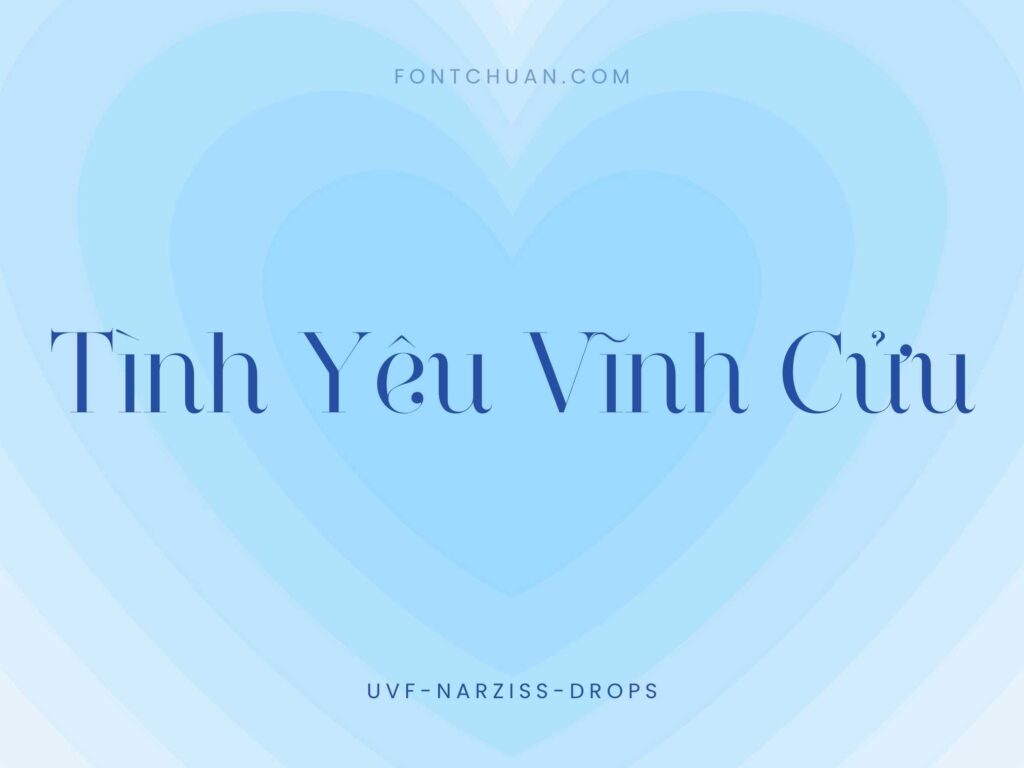
Font UVF Narzissdrops Việt Hóa
Narziss Drops là một phông chữ serif độc đáo và đầy nghệ thuật, được thiết kế bởi Hubert Jocham. Phông chữ này nổi bật với các chi tiết trang trí phức tạp và nét thanh đậm xen kẽ, tạo ra một phong cách sang trọng, lãng mạn và quyến rũ. Đặc điểm hình dạng của Narziss Drops là các đường nét hoa mỹ, uốn lượn tinh tế và sự kết hợp giữa các yếu tố truyền thống và hiện đại, giúp tối ưu hóa không gian và tạo ấn tượng thị giác mạnh mẽ.
Font này phù hợp cho các ứng dụng như thiệp mời, logo thương hiệu cao cấp, bìa sách, hoặc các ấn phẩm đặc biệt, nơi cần tạo ra sự ấn tượng mạnh mẽ về thị giác và cảm xúc. Trong lĩnh vực sự kiện, Narziss Drops có thể được sử dụng trong các dịp như lễ hội, lễ cưới và các sự kiện văn hóa. Ngoài ra, font này cũng thích hợp cho các ngành nghề như thiết kế đồ họa, nghệ thuật trang trí và xuất bản.
Bên cạnh các ứng dụng sang trọng và nghệ thuật, Narziss Drops còn là một font valentine lý tưởng để thiết kế các sản phẩm lãng mạn và ngọt ngào, như thiệp Valentine, banner hay poster dịp lễ tình nhân. Với các đường nét uốn lượn tinh tế, chi tiết hoa mỹ và phong cách lãng mạn, font này giúp các thiết kế vừa quyến rũ, vừa mang cảm giác ấm áp, phù hợp cho các dự án sáng tạo về tình yêu và các dịp đặc biệt.